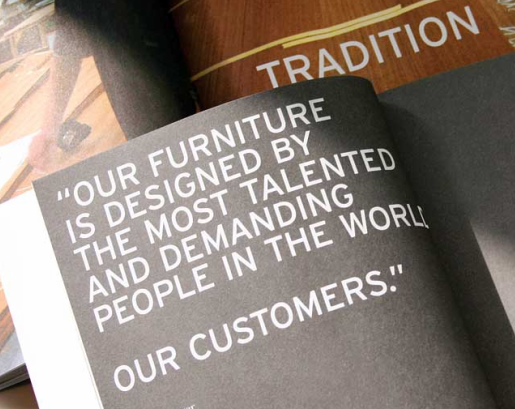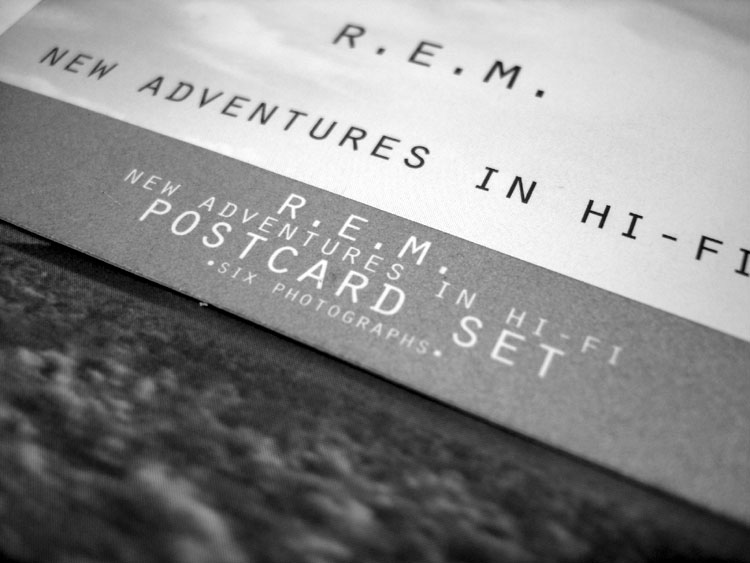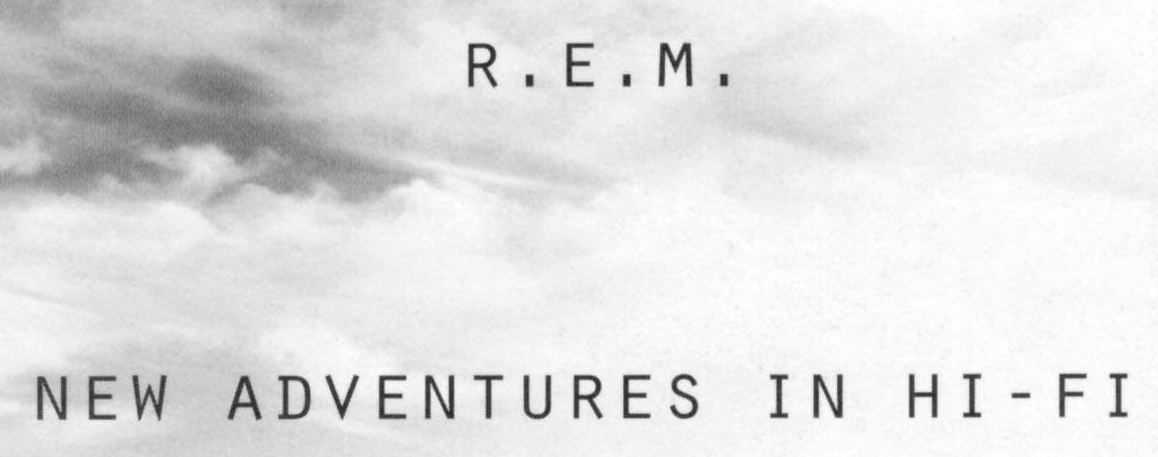
Suche zwei Schriftarten.
ich suche zwei Schriftarten. Dürfte für Euch aber nicht allzu schwierig sein.
1. Diese hier geht ein bißchen in die Gotham Richtung. Erkennt die jemand? Kann das womöglich die Interstate sein? Die kenn ich nicht so gut.
2. Diese Monospace Schrift hab ich schon mal gesehen. Sie erinnert mich an die Letter Gothic, aber diese Serifen am D irritieren mich gerade. Ist das eine Abwandlung der Letter Gothic?
Hier ein größeres unverzerrtes Bild:
Letter Gothic. Es gibt es auf CTAN (Comprehensive TeX Archive Network, zB ftp://ftp.dante.de/) eine freie Version von URW in Regular und Italic. Hier aus dem README (um Zweifel an der Korrektheit des Downloads zu entkräften):
Das sind wohl die Kapitälchen der Orator:
Ich glaube, das Original von IBM gab’s nur mit Kapitälchen. Bitstream bietet die Schrift mit Kleinbuchstaben an, aber die sind wohl nachträglich entstanden.
Zum Original von IBM gibt es in den ,,100 Besten Schriften'' von Fontfont einen kurzen Abriss.